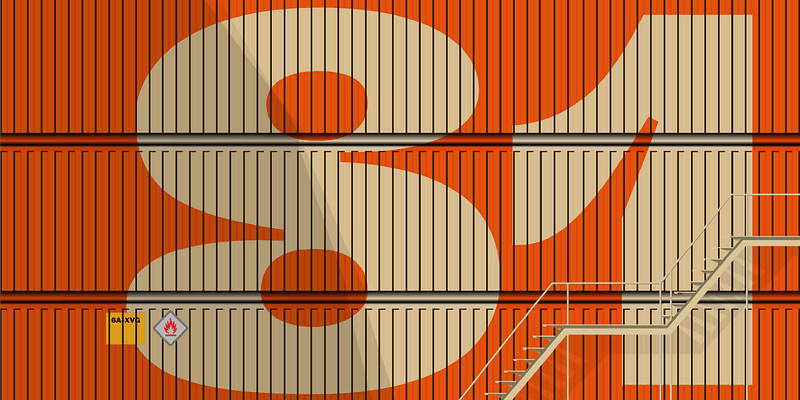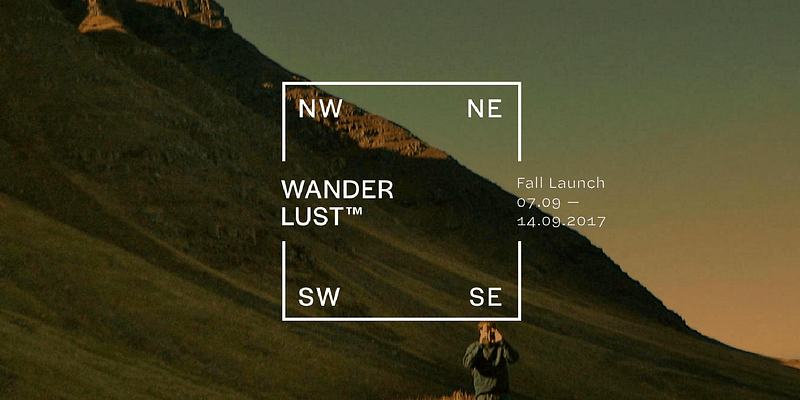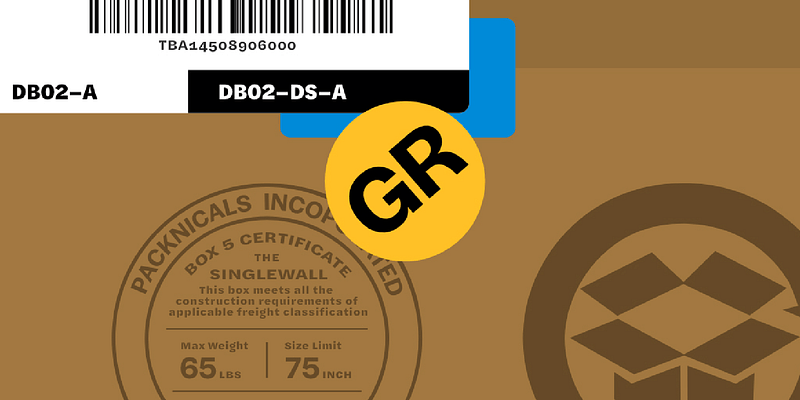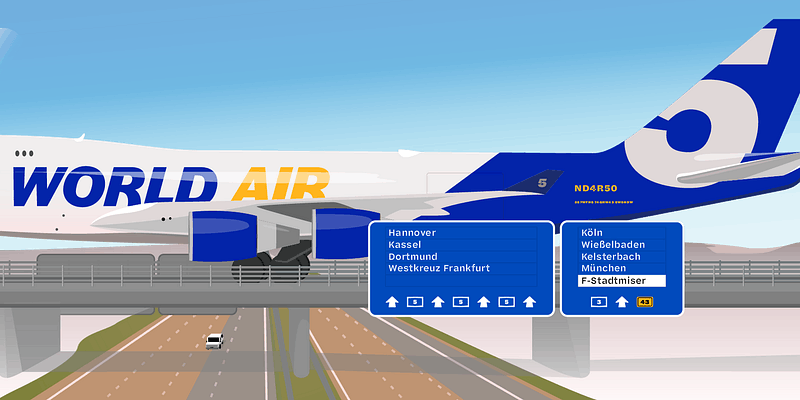
Halyard erweitert radikal den typografischen Nutzen der inzwischen allgegenwärtigen Kategorie Grotesque Sans. Die Persönlichkeit von Halyard ist gleichzeitig vertraut und angenehm unverwechselbar. Die Halyard-Superfamilie ist wunderbar robust und lebendig und kann in jeder Größe eingesetzt werden. Die optischen Unterfamilien von Halyard unterscheiden sich zwar in ihrer Erscheinung stark voneinander, wirken aber in den vorgesehenen Größen mit einer konsistenten Persönlichkeit und erwecken den Eindruck eines einzigen Schriftdesigns.